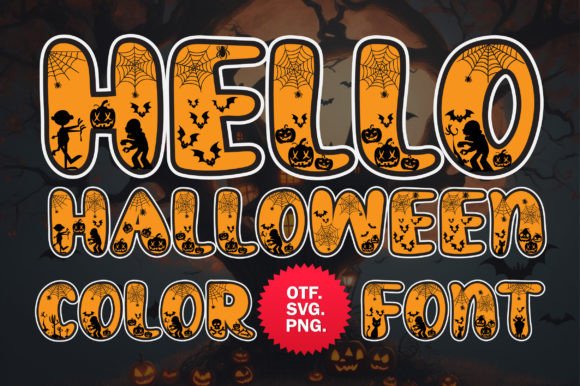
Hello Halloween Font
Hello Halloween Font – الخط المثالي لأجواء الهالوين! ????????
أضف لمسة سحرية ومرعبة إلى تصاميمك مع Hello Halloween Font! يتميز هذا الخط بأسلوبه الفريد المستوحى من أجواء الهالوين الغامضة، مما يجعله مثاليًا لمشاريع التصميم المرعبة والممتعة.
???? المميزات:
✅ تصميم فريد مستوحى من الهالوين ????
✅ يدعم الحروف الكبيرة والصغيرة ✍️
✅ مناسب للبوسترات، الدعوات، الشعارات، والتيشيرتات والمزيد!
اجعل تصاميمك أكثر إبداعًا ورعبًا مع Hello Halloween Font! ????✨